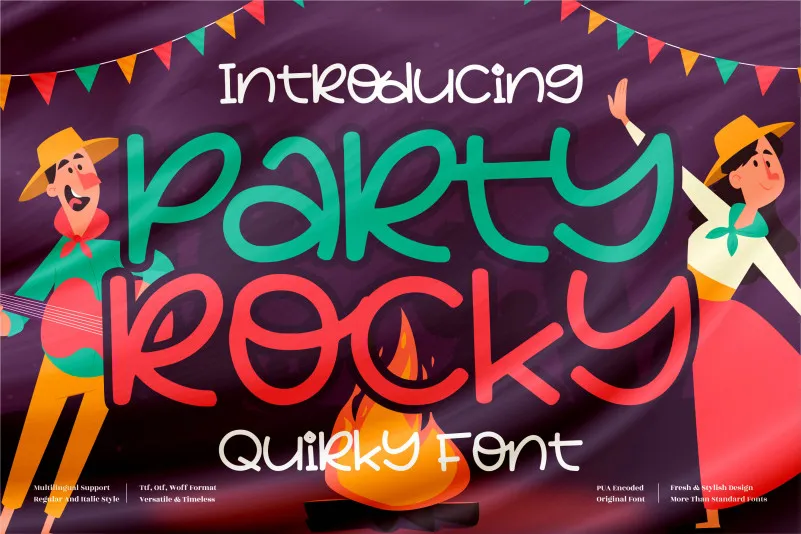
A Party Rocky Font é uma elegante escolha para quem procura uma fonte com personalidade e originalidade. Criada pelo designer perspectype, esta aberta é adequada para diversos projetos de design visual. Seja para criar um logo único, decorar artigos de casa, embalagens de produtos ou até mesmo adicionar um toque especial a sua capa de livro, essa fonte vai fornecer aquele brilho único que você busca. A Party Rocky Font tem uma identidade própria e uma cara fresca, especialmente adequada para aplicativos em materiais como mugs, etiquetas, camisas, cartões de nome, convites ou até mesmo embalagens de produtos. Suas linhas livres e alegres são perfeitas para adicionar um toque divertido aos seus trabalhos, tornando-os uma representação única que chama a atenção. Seja qual for o seu projeto, seja ele personalizado em cartazes, etiquetas ou até mesmo na capa de um livro, esta fonte trará aquela graça casual e encantadora característica que torna cada design único.